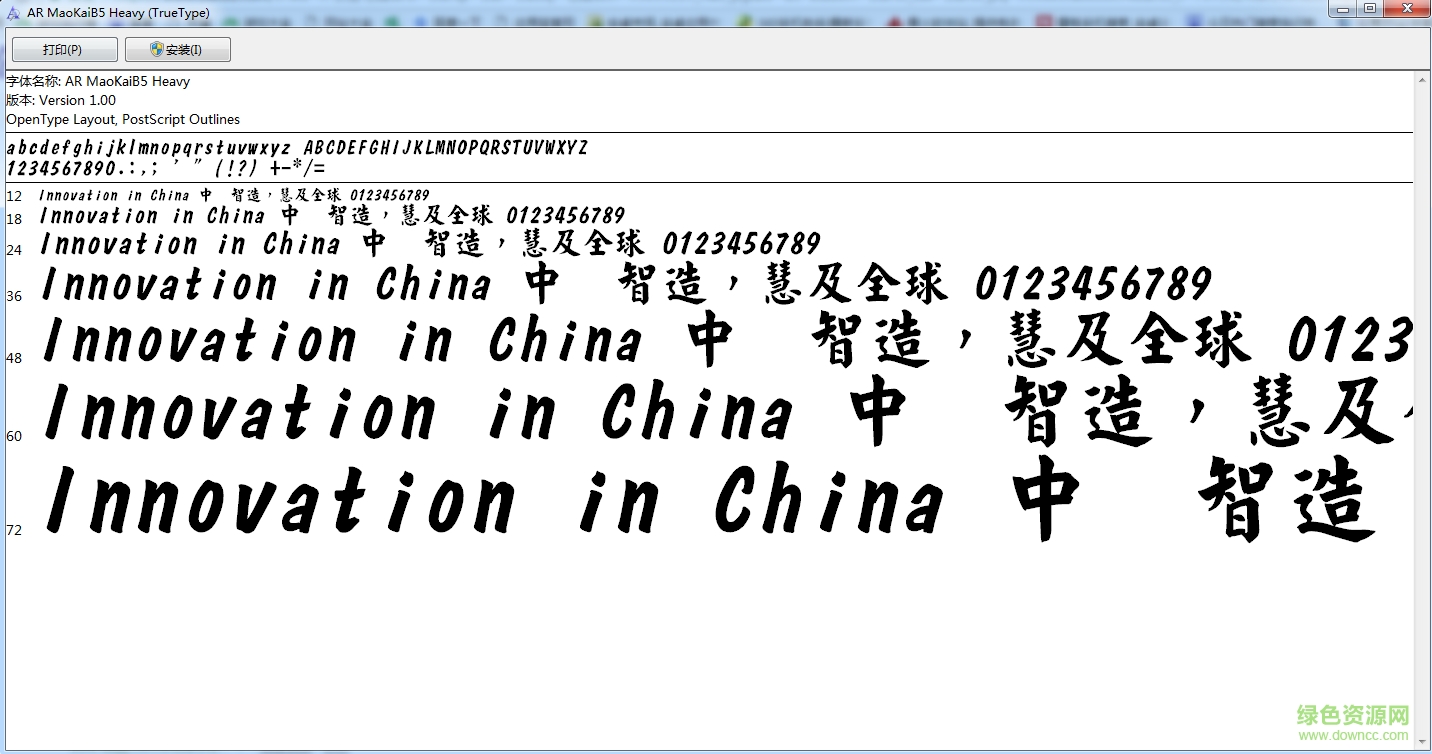
軟件介紹 軟件標簽: 文鼎字體 字體 文鼎特毛楷體是同時融合了毛筆書法和楷書特點的文鼎字體,該字體運筆靈活,筆畫生動,字形清秀俊,十分美觀,朗歡迎大家免費下載!楷書字體特點點畫準確精到,結構疏密得當,結體寬綽開張,點畫規(guī)矩清楚;結密無間而氣魄宏闊,不致渙散無神。文鼎特毛楷安裝說明Win 7\Win 8\Win 10系統(tǒng) : 鼠標右鍵單擊字體文件,然后點擊 > "Install" 安裝字體Win XP(2000\98)系統(tǒng) : 把解壓好的字體文件放入 C:\Windows\Fonts 目錄中即可 軟件截圖 上一張下一張(1 / 1) 安裝詳細截圖 猜你喜歡 楷書字體 楷書字體 楷書字體是綠色資源網(wǎng)小編專為大家收集的一類非常流行而且好用的楷書字體,它包括了各種形式的楷書。楷書也叫正楷、真書、正書。從程邈創(chuàng)立的隸書逐漸演變而來,更趨簡化,橫平豎直,筆勢雄奇,姿態(tài)橫生,可應用于繪畫設計、藝術創(chuàng)作、平面廣告、印刷包裝、電視廣告等等各行各業(yè)。也是現(xiàn)在很多行業(yè)必用的一類字體,小編收集的這一類楷書字體希望能更好的幫助大家收集和使用楷書字體。 查看更多>> 楷體國標字體官方版 2.45M/中文/7.1/下載 漢儀閃耀楷書字體 1.77M/中文/0.0/下載 華為漢儀錦時楷書 2.92M/中文/5.0/下載 楷書字典手機版 4.46M/中文/5.0/v2.0 安卓版下載 經(jīng)典楷體繁體 3.96M/中文/5.0/下載 楷書繁體字體包 9.76M/中文/8.0/下載 其他版本下載 標題 大小 更新日期 下載 下載地址 電腦版 文鼎特毛楷體 點擊報錯 軟件無法下載或下載后無法使用,請點擊報錯,謝謝! 關閉報錯反饋 請描述您所遇到的錯誤,我們將盡快予以修正,謝謝! *必填項,請輸入內容 本類最新 經(jīng)典繁方新 緇忓吀緇嗗渾綆 regutar 94款經(jīng)典字體打包 免費版 經(jīng)典行書簡 經(jīng)典圖案字字體 經(jīng)典特宋簡體 相關文章 Photoshop字體安裝使用方法和技巧 如何解決“無法新增字體”問題 Win 7系統(tǒng)安裝字體方法 網(wǎng)頁字體大小設置方法 怎么改網(wǎng)頁字體大小 在Linux系統(tǒng)中安裝字體的幾種方法 windows7字體顯示問題:打開某些程序的時候顯示的是亂碼 用戶評論 熱門評論 最新評論 發(fā)表評論 查看所有評論(0) 昵稱: 請不要評論無意義或臟話,我們所有評論會有人工審核. 字數(shù): 0/500 (您的評論需要經(jīng)過審核才能顯示)